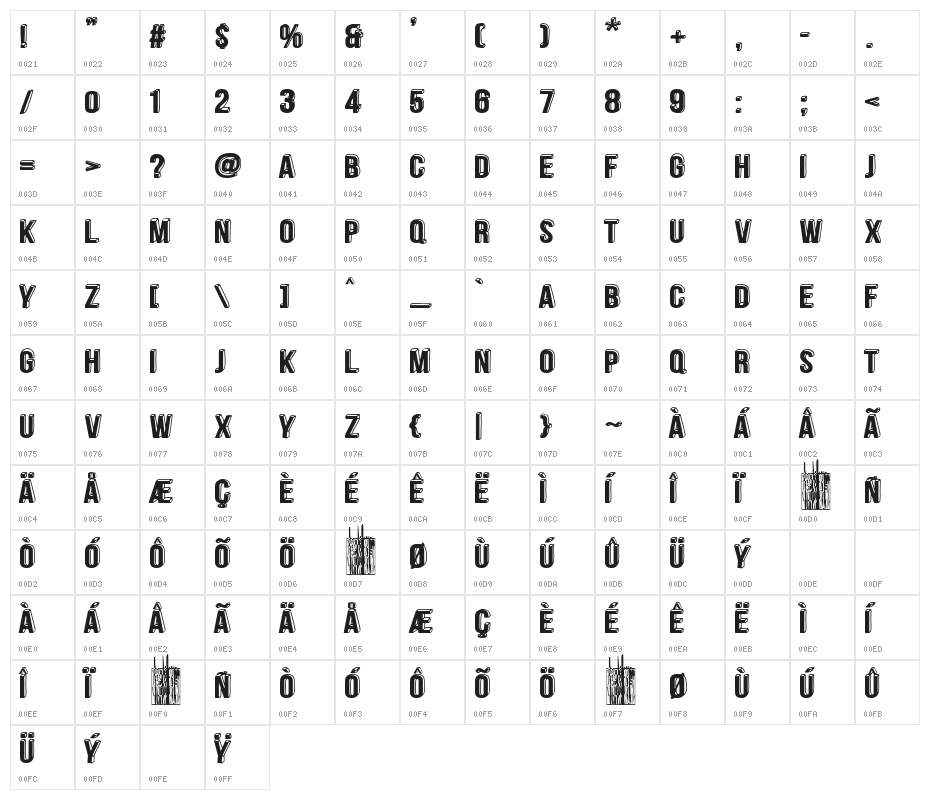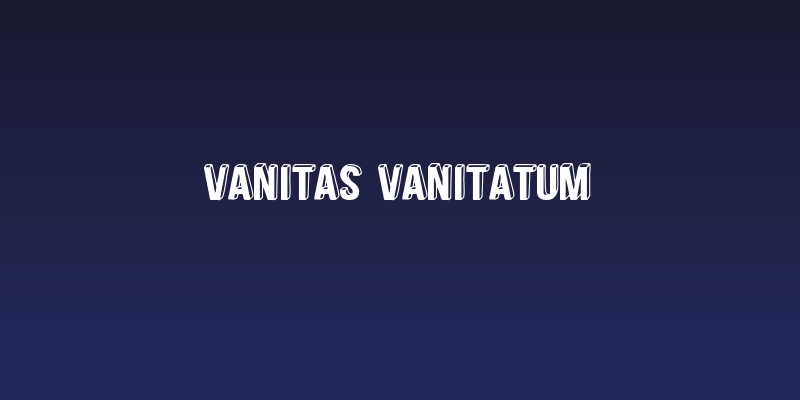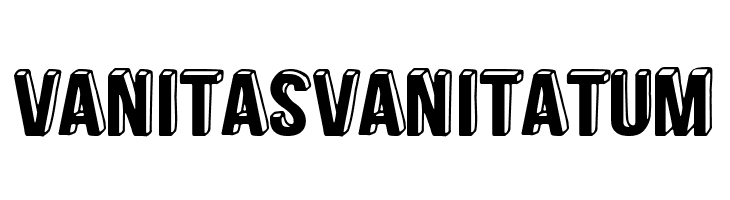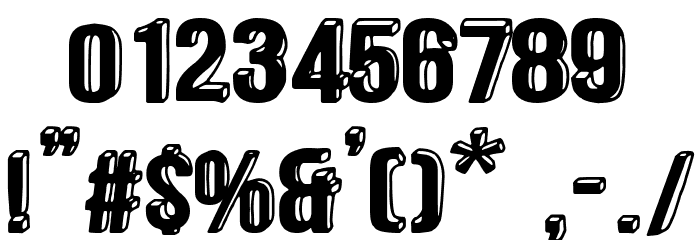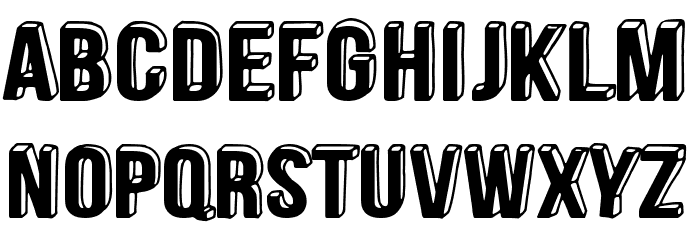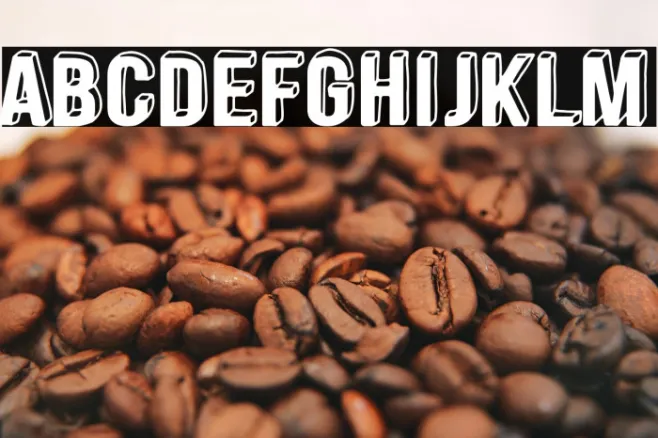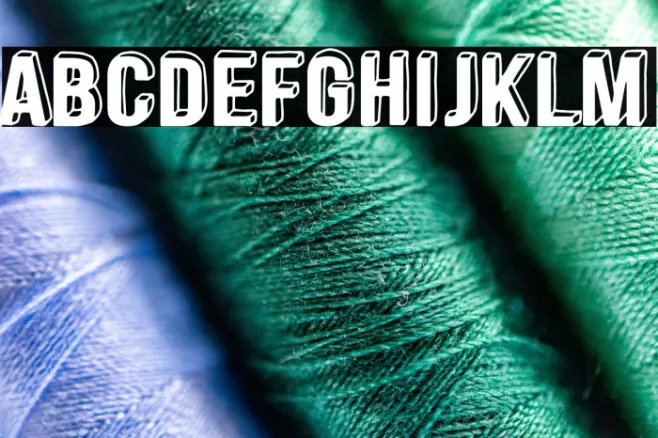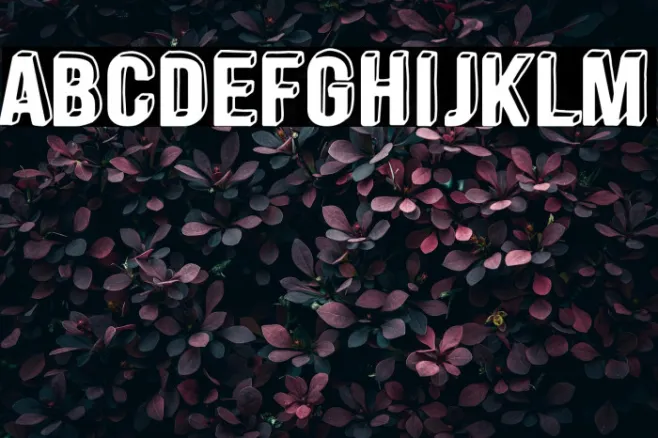
Vanitas Vanitatum Font
| Gesamtstil | Decorative, Retro, Playful |
| Anwendungsfall | Headlines, Posters, Logos, Event Promotions |
| Vorgeschlagene Projekte | Posters, event flyers, branding for entertainment or nightlife, retro-themed designs, headlines. |
Vanitas Vanitatum